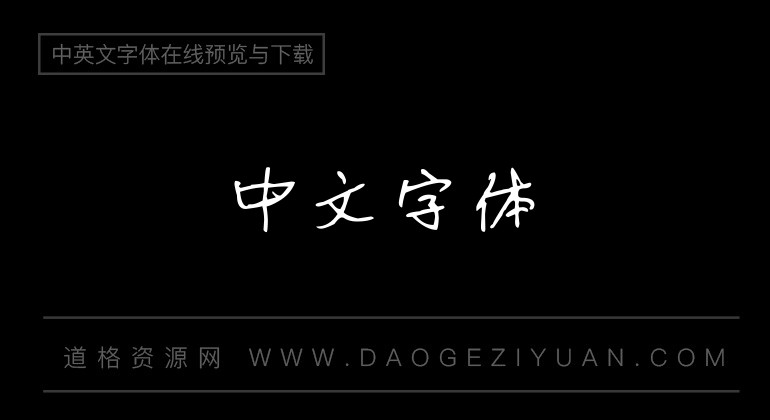
书体坊硬笔行书3500字体是一款古风书法字体,以清朝书法家黄庭坚的行书为原型,经过精心设计和细致制作而成。它具有传统行书的笔画结构,字形清晰,笔画流畅,层次感强,笔锋有力,表现力强,让人眼前一亮。此外,它还具有良好的可读性,可以让读者更容易地阅读文字,让文字更加美观大方。文件名:ShuTiFangYingBiXingShu3500-1.ttf
书体坊硬笔行书3500是一款非常不错的手写艺术字体,具有很好的视觉感,适合于文化类的宣传设计、商业类品牌的广告和产品包装设计以及个性化文字排版等较多场景。